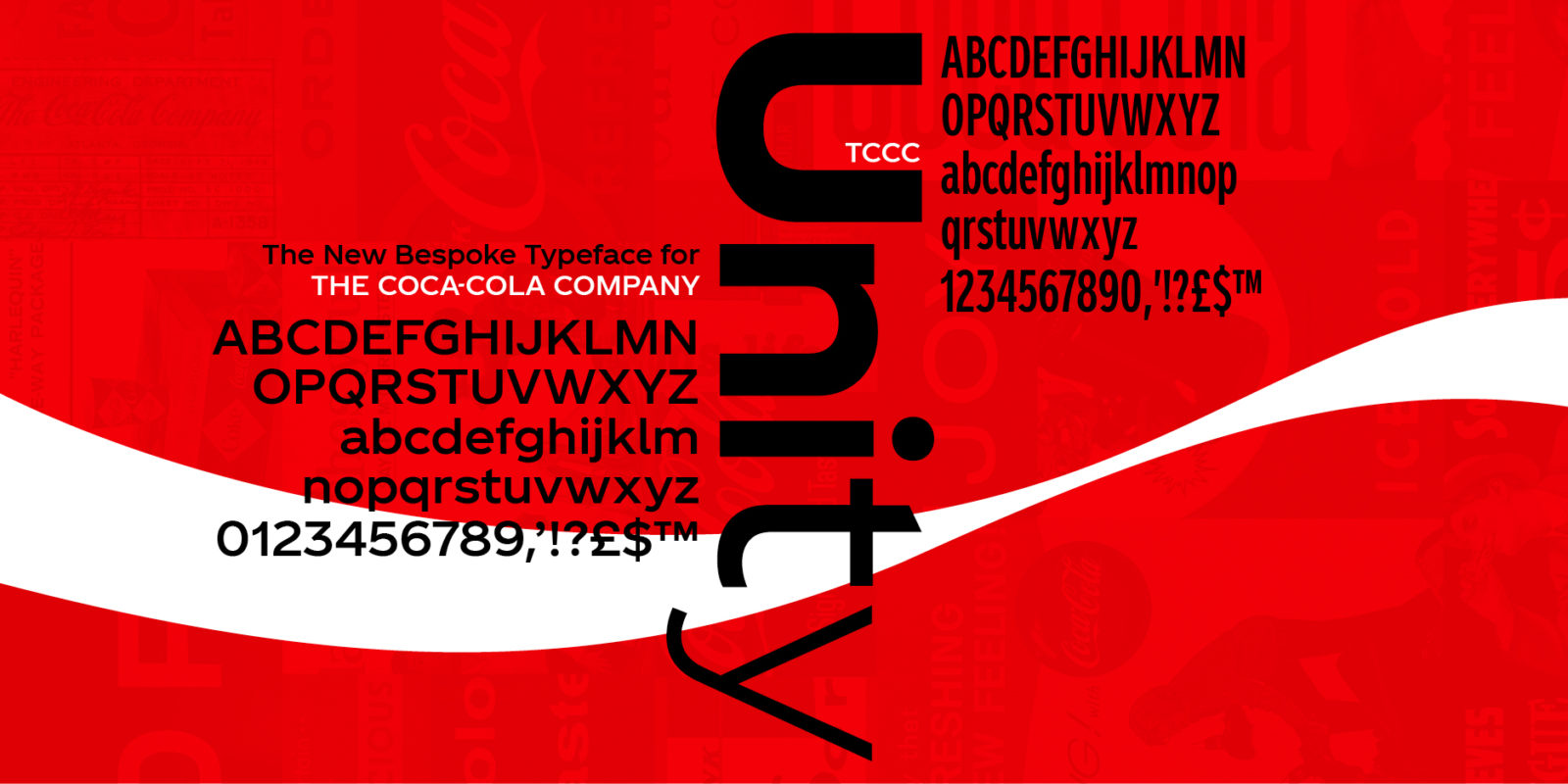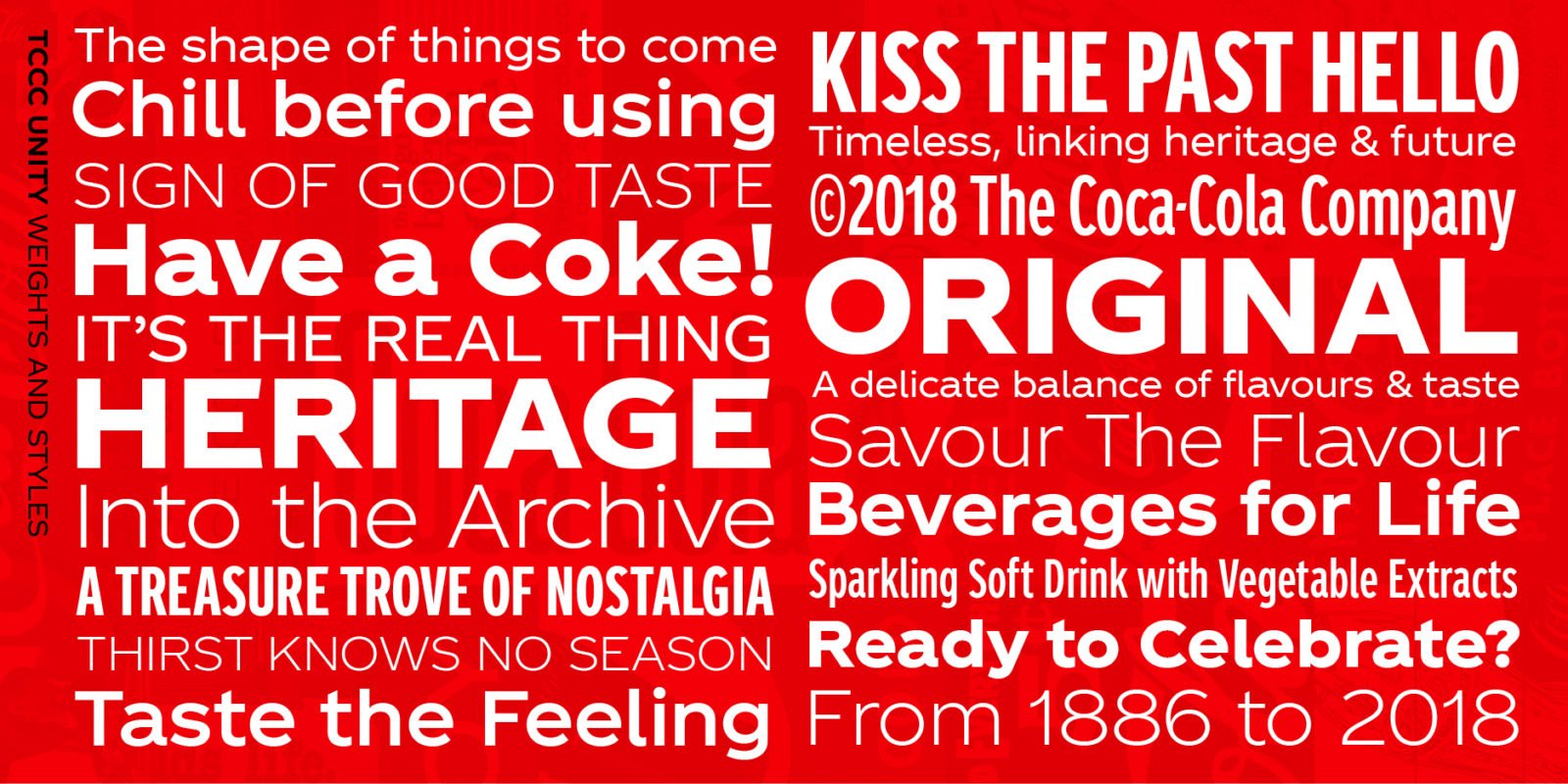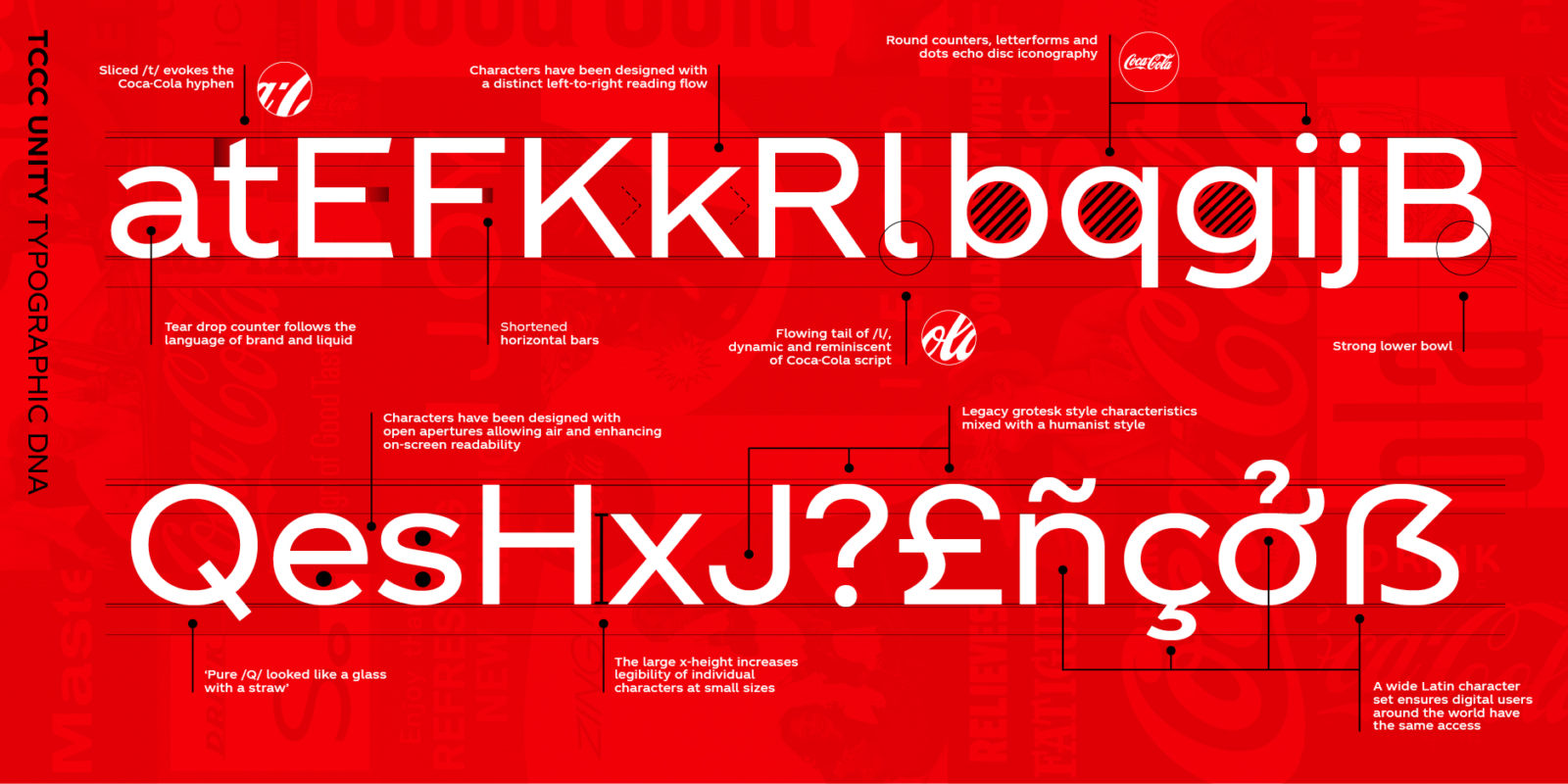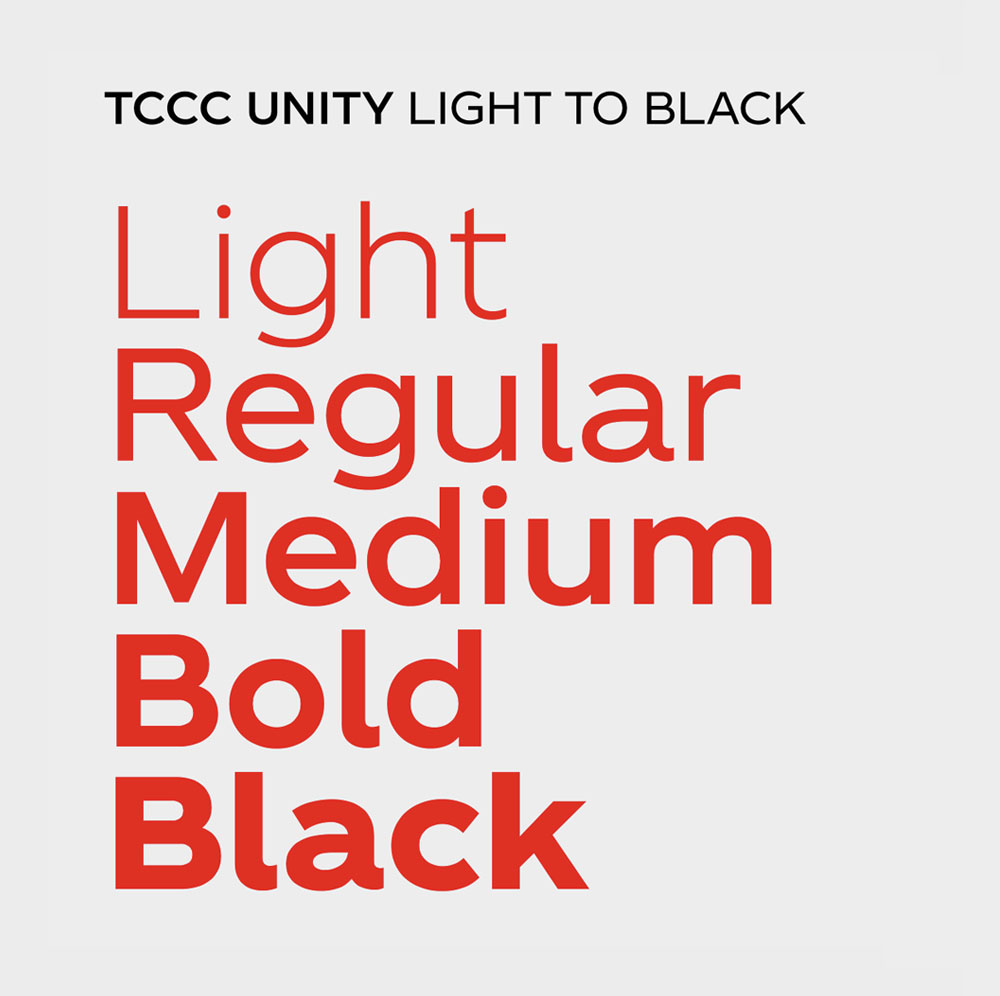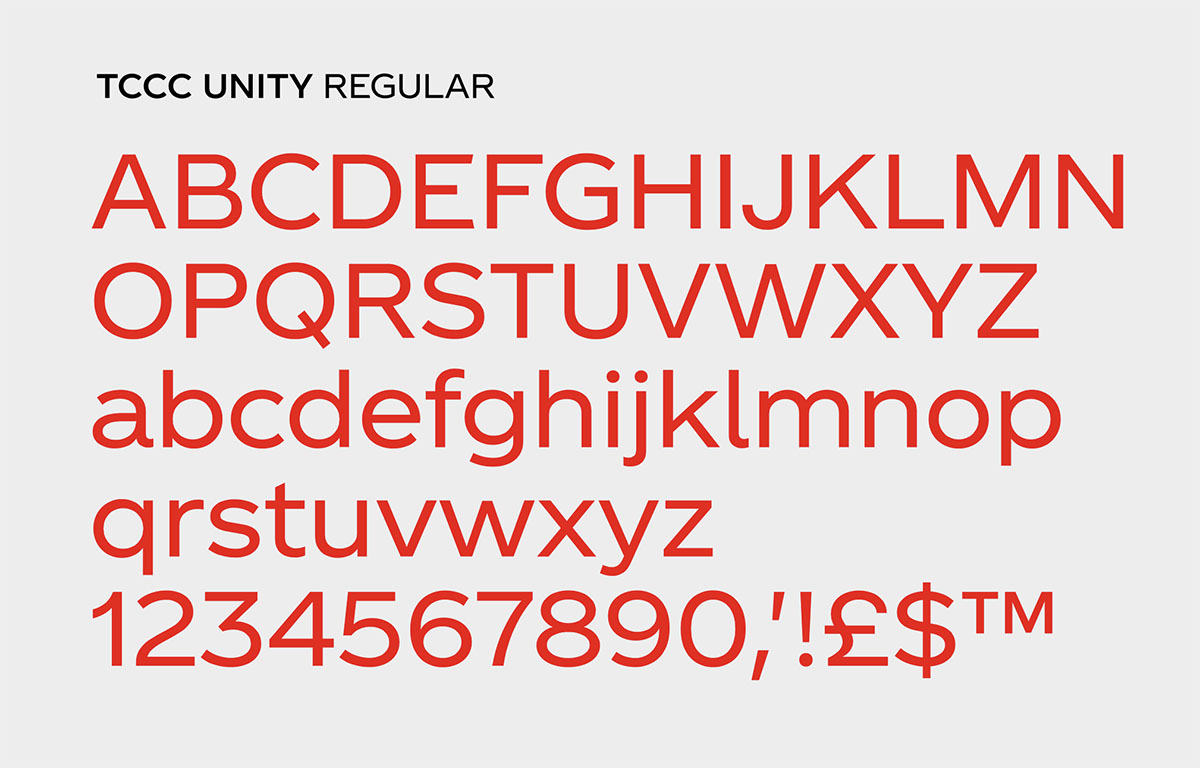
Coca Cola ed il suo nuovo Typeface
É stato presentato ad Atlanta, da James Somerville, vice presidente globale del settore design di Coca Cola.  Il designer: una garanzia. Neville Brody, il volto dei magazine “The Face” e “Fuse”, autore di moltissimi caratteri nel corso degli anni ’80 e ’90, ma che ha dimostrato che il suo lavoro si è evoluto assieme a lui, nel corso dei decenni.
TCCC unity
“The Coca Cola Company Unity”, il nome di questo carattere, progettato da Brody e dal design team Coca Cola.
Prodotto in svariati pesi e stili, garantisce una vasta versatilità e flessibilità, permettendo all’azienda di far evolvere il proprio linguaggio visivo su tutte le piattaforme.
Un carattere che dovrà essere usato, infatti, sia sul web che sui prodotti stampati, dalle ADV ai pack, passando per tutte le declinazioni intermedie.
Tra le influenze che hanno giocato un ruolo primario, nell’ispirare questo carattere, l’america dei ’30 e ’50, con la sua tipografia di velocità e modernità. Disegnato con forme aperte, larghe, estese. Come l’America moderna.
In termini di funzionalità, come già accennato, attraverso lo sbiluppo di due versioni “text” e “display”, il carattere opererà in maniera costante su ogni piattaforme, per acquisire, con la sua personalità, una buona riconoscibilità da parte del pubblico.
Intervistato da Print Magazine, Brody racconta il processo che lo ha portato alla realizzazione del carattere.
Il processo creativo ha visto una forte collaborazione con il design team di Coca Cola, guidato da James Sommerville, che ha chiesto un carattere moderno, in grado di essere ottimizzato su ogni piattaforma corrente e futura e di spaziare agilmente tra un ambiente web ed uno stampa.
Le focus keyword sono state dunque “Scalable”, “Ownable” e “Recognizable” con un alto livello di leggibilità.
Importante considerare che, nel corso di  130 anni di storia, i prodotti Coca Cola sono stati rinnovati nel colore, nella forma e nel gusto. Ma mai era stato disegnato un font proprietario riconducibile esclusivamente al brand.
Basandosi dunque, su un enorme quantità di assets, workshop e meeting, il team ha lavorato fianco a fianco con le varie strutture Coca Cola nel mondo, ispezionando migliaia di oggetti e prototipi passati e recenti.
Sono molto soddisfatto del lavoro. – Racconta Brody – É stata una grande sfida, ma abbiamo progettato un carattere che durerà negli anni e sono convinto che sia forte, accessibile e che rispecchi a pieno il band. Ad essere onesto, aver realizzato il primo carattere proprietario di Coca Cola è davvero fantastico!
Una sfida. Un obiettivo. Un  processo creativo che viene narrato, durante la presentazione del Typeface. Del resto, il trend del momento è proprio lo storytelling.
Se si tratta di Coca Cola, poi, che è globalmente riconosciuta come una delle aziende pioniere in questo settore, non si poteva che aspettarsi un grande lavoro volto a spiegare ogni fase creativa e progettuale.
Un progetto ambizioso, che mette in discussione la filosofia e la personalità di un brand internazionale.
E di cui, solo il tempo saprà mostrare i frutti.